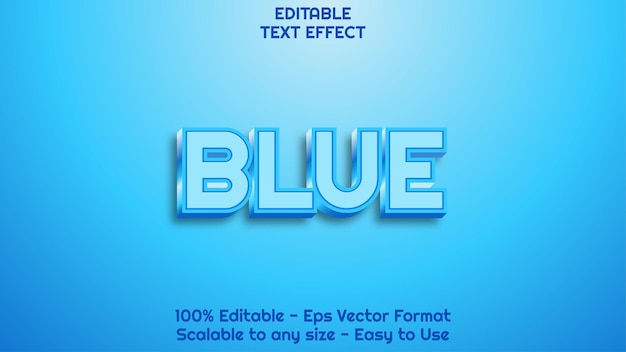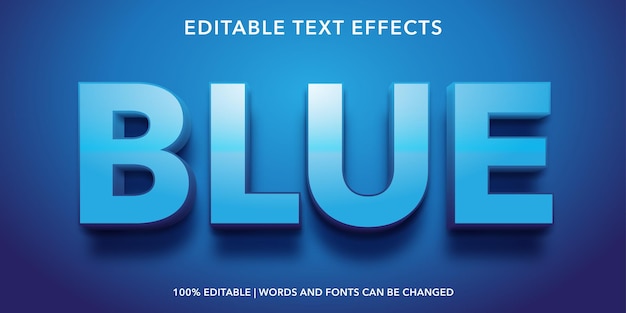
Векторный редактируемый синий шрифт типография шаблон текстовый эффект стиль шрифт шрифт стильВекторный редактируемый синий шрифт типография шаблон текстовый эффект стиль шрифт шрифт стиль
Векторный редактируемый синий шрифт типография шаблон текстовый эффект стиль шрифт шрифт стиль